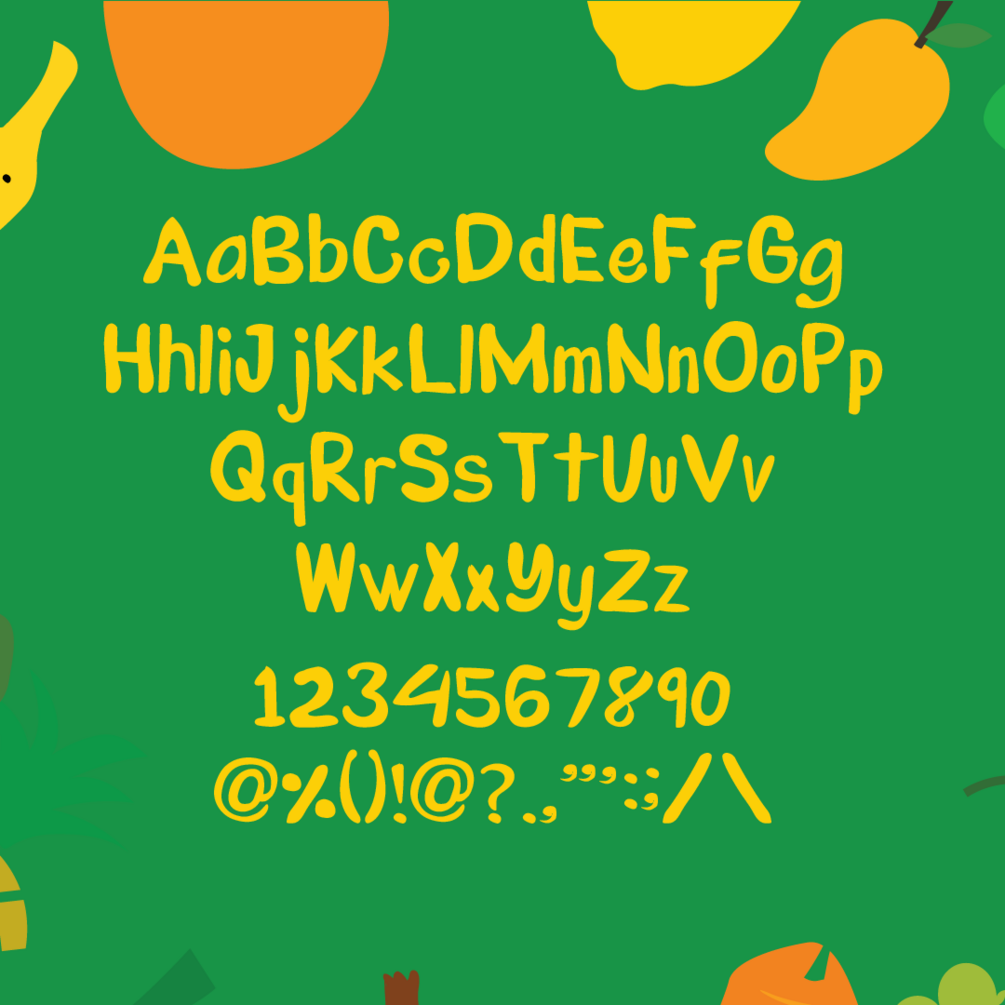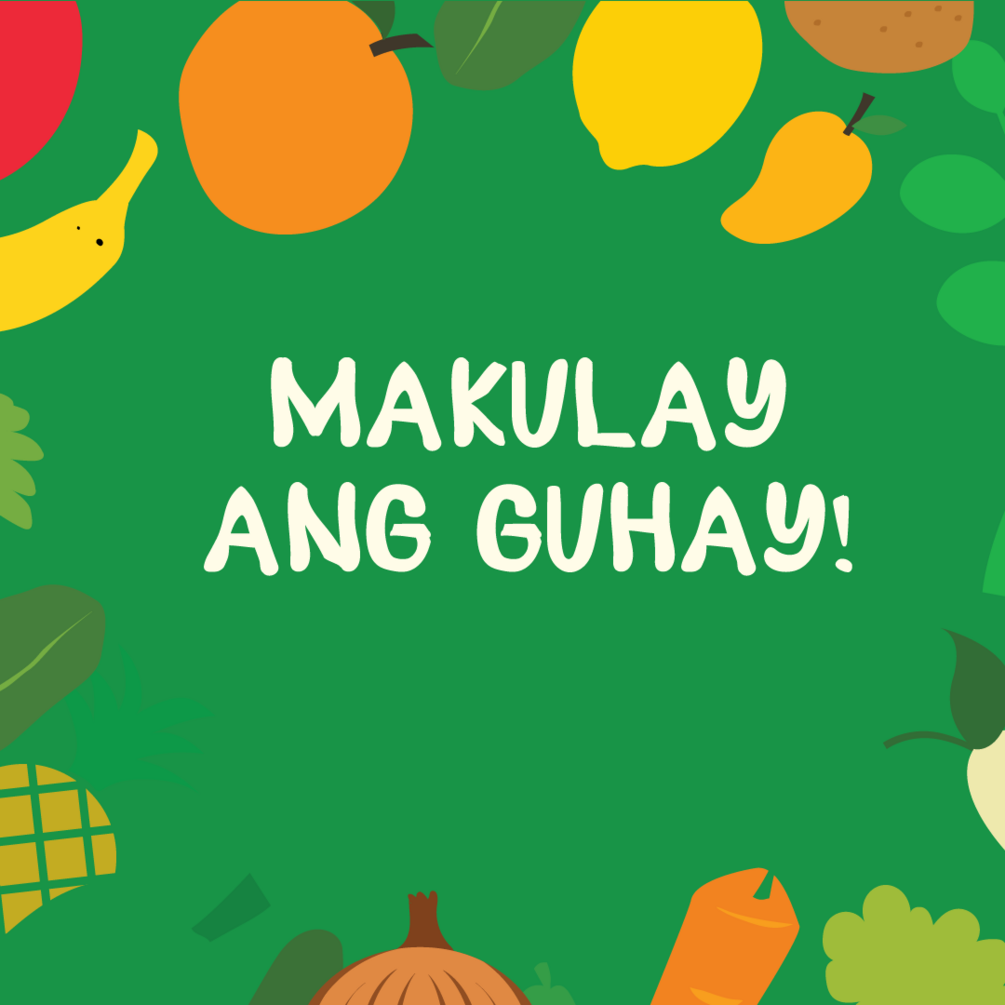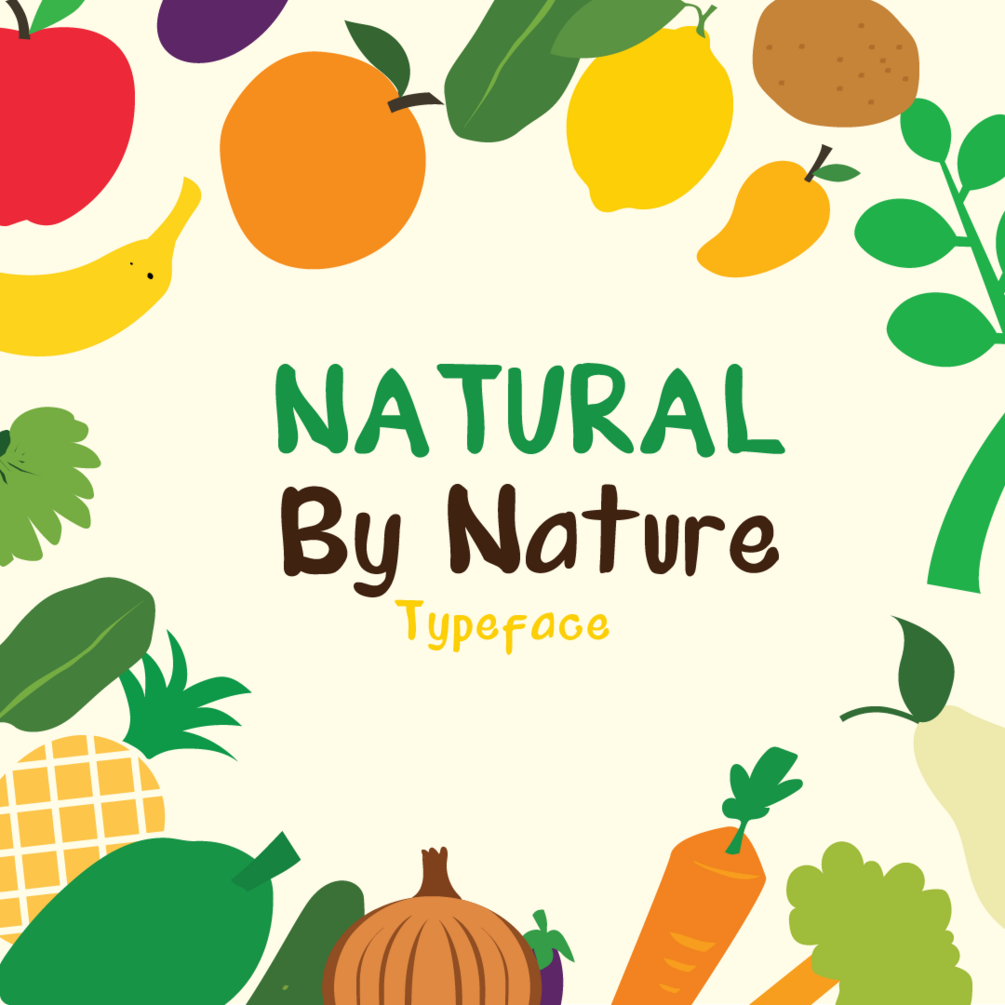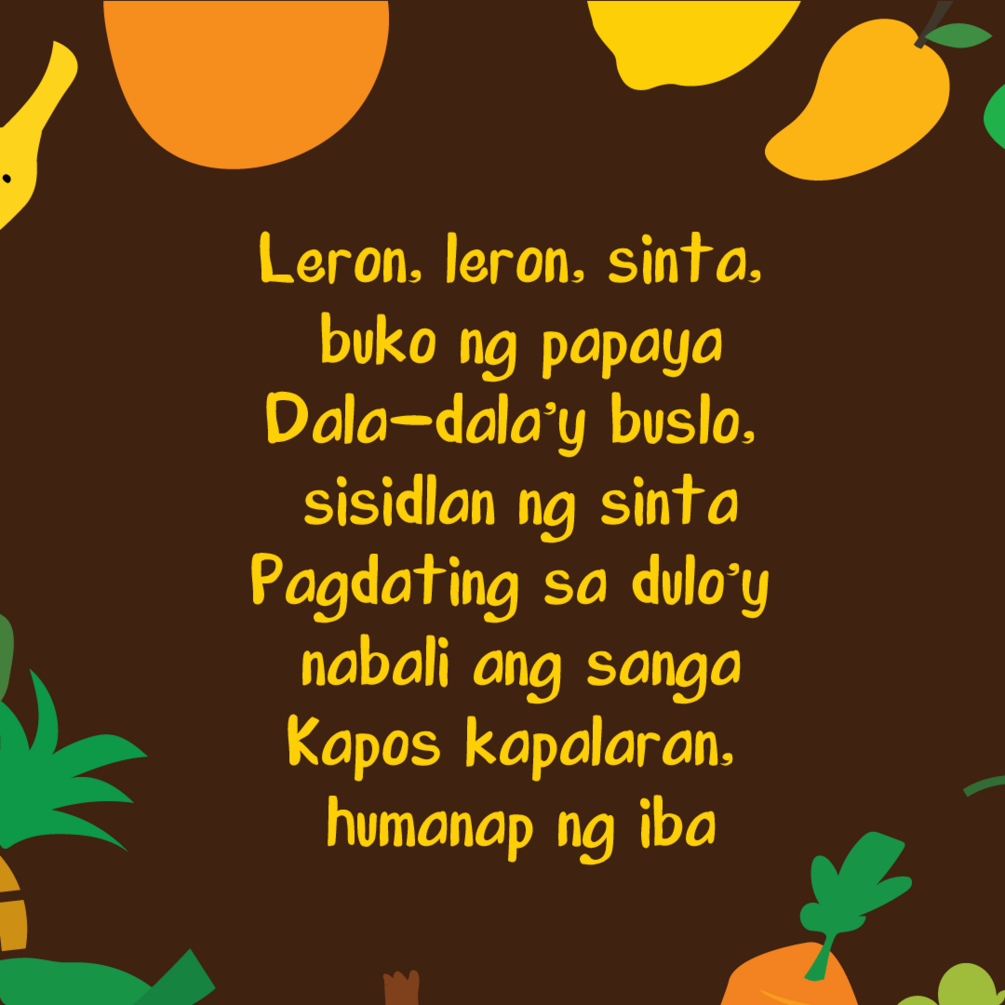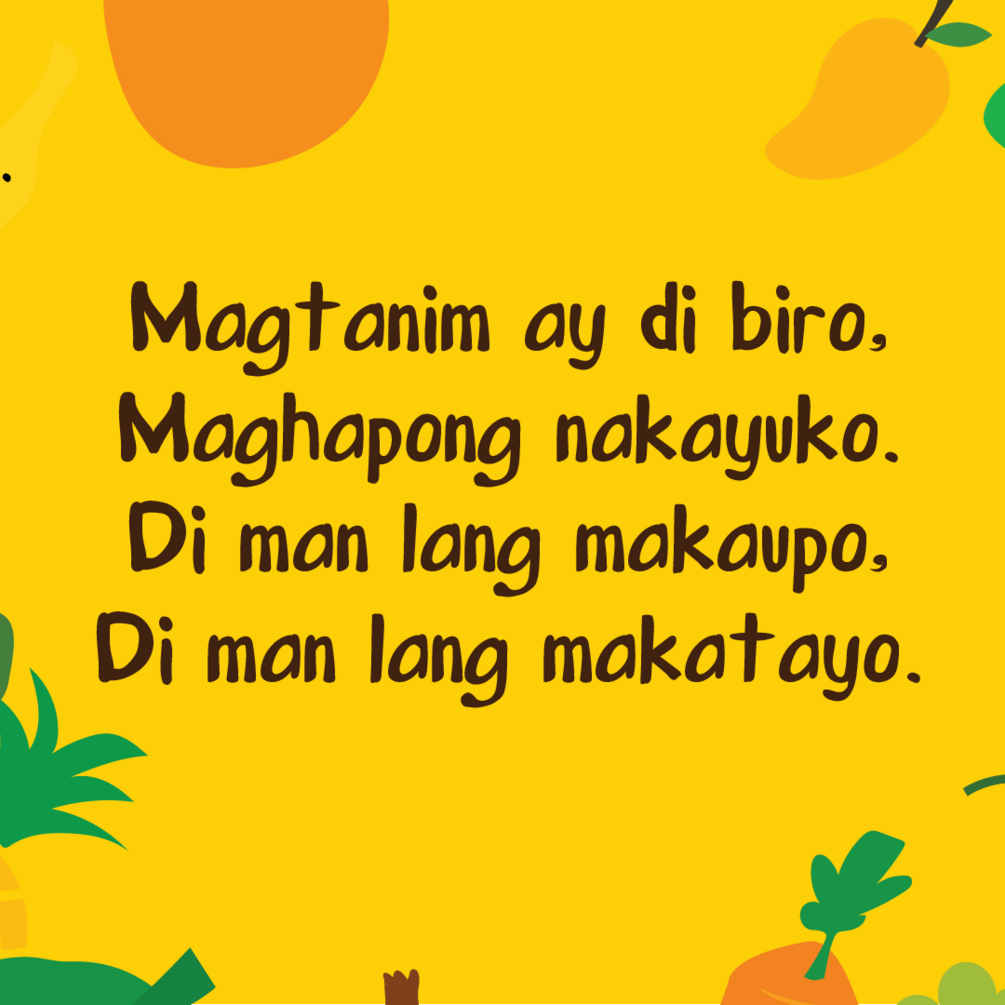
Natural by Nature
Gawing natural ang buhay gamit ang natural na tipo. Ang Natural by nature ay gawa ito galing sa walang hintong pagtatanim at pagbibigay pagkain mula sa ating mga farmers. Kaya dapat lang mahalin at gawing natural ang pagpupugay sa kanila.
Magtanim ay di biro.